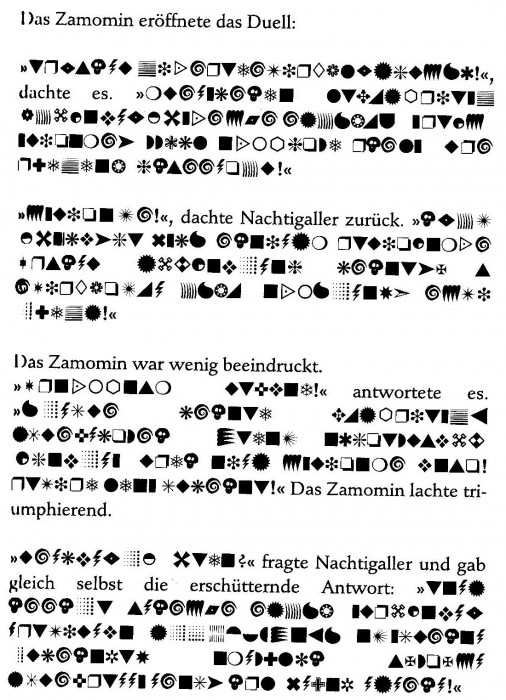
Suche Symbolschrift
ich habe dieses Beispiel aus dem Buch "Die 13 1/2 Leben des Käpt'n Blaubär" (1999) von Walter Moers und wüsste gerne, um welche Schriftart es sich denn bei den Symbolen handelt.
Ich weiß, das ist bestimmt, sehr schwer rauszukriegen, aber ich dachte, ich frag einfach mal.
Ich habe fast den Eindruck, dass es sich um unterschiedliche Dingbats-Fonts handelt, da sie stilistisch recht stark differieren … Einige der Symbole davon kommen zum Beispiel in der Zapf Dingbats vor.
Wenn Du bei den gängigen Schriftenanbietern (zum Beispiel www.myfonts.com) das Suchwort »Dingbats« eingibst, dann erhältst Du eine Vielzahl solcher Symbolschriften angezeigt und kannst dann mit Deinem Muster vergleichen.
Dass der Knaus Verlag eine dafont-Schrift verwendet hat, halte ich aber eher für unwahrscheinlich.
Die Seite ist übrigens in google books als Buch-Auszug zu finden, eventuell kann jemand durch den Quelltext etc. herausfinden, welcher Font das sein mag (falls die Seiten nicht als Bild ausgeliefert werden …).